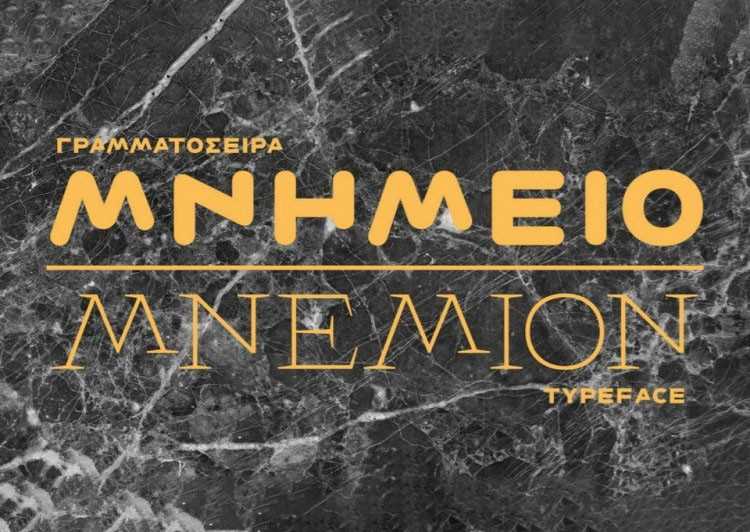
Mnemion Font – Fonte Grátis
Mnemion Font
A fonte Mnemion é um encantador conjunto de serifada para ambientes visuais que valorizam a exibição à distância. Desenvolvida pelo 99designs, ela mergulha nos mistérios do design tipográfico ao cruzar os horizontes estilísticos e morfológicos entre diferentes eras históricas e scripts. Inspirada nas influências antigo-românticas, o desenho da fonte percorre desde a antiguidade até o início do século XX, explorando as transformações de estilo que o tempo pode trazer às letras. O resultado é uma tipografia vibrante, capaz de destacar qualquer design e mesmo, em alguns momentos, provocativa por sua originalidade. Com três variáveis principais: Arcaica, Roman e Modern, a fonte Mnemion oferece um leque amplo de possibilidades para designers que buscam estilos únicos e distintos. Ela é uma escolha perfeita para aqueles buscando adicionar sutileza sofisticada ou elegância clássica aos seus projetos visuais, permitindo que cada elemento do design seja destacado e ressaltado através de sua própria personalidade única.